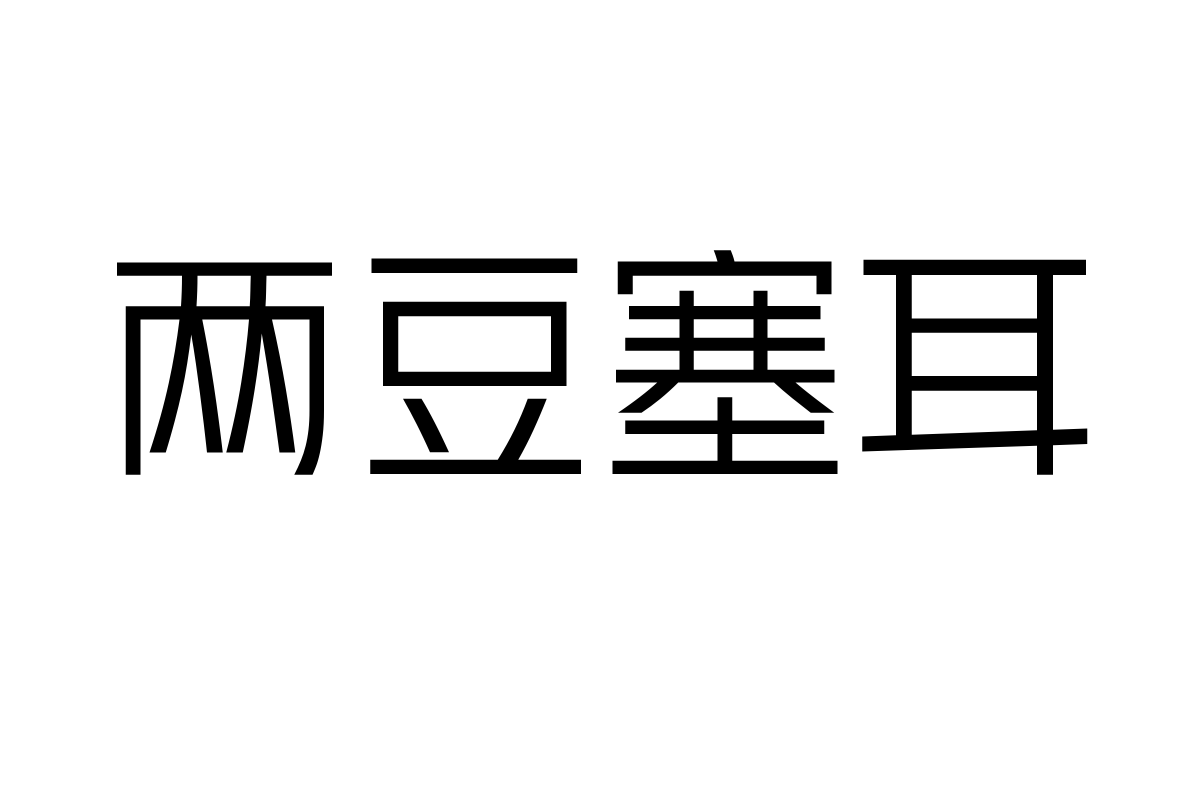
汉仪雅酷黑-45 是一款现代而优雅的黑体字体,具有强烈的视觉冲击力和辨识度。这款字体采用了独特的设计元素,使其在众多字体中脱颖而出。其笔画流畅、结构紧凑,给人一种简洁明了的感觉。同时,它的字形大小适中,适合用于各种印刷品和网页设计。无论是标题、正文还是装饰性文字,都能轻松驾驭。此外,汉仪雅酷黑-45 还具有很好的可读性和易用性,适合用于需要强调文字内容的设计作品。